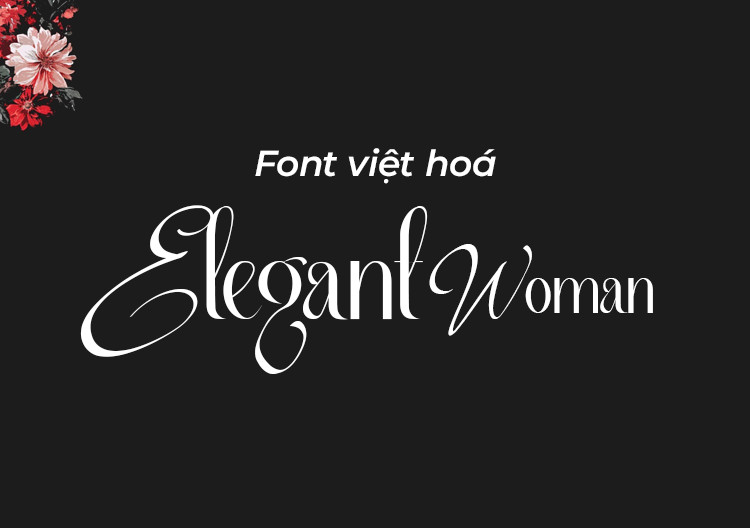
Giới thiệu về Font việt hóa MJ Elegant Woman
Trong thế giới đồ họa hiện đại, việc lựa chọn Font Chữ phù hợp đóng vai trò quyết định đến linh hồn của tác phẩm. Font việt hóa MJ Elegant Woman là một bộ font Serif (có chân) mang phong cách cổ điển, quý phái nhưng không kém phần hiện đại. Được thiết kế với những đường nét mảnh mai, uốn lượn tinh tế, bộ font này mô phỏng vẻ đẹp mềm mại của người phụ nữ, giúp các bản thiết kế trở nên sang trọng và thu hút hơn bao giờ hết.
Đặc điểm nổi bật của bộ font
Bộ font này sở hữu độ tương phản cao giữa các nét thanh và nét đậm, tạo nên nhịp điệu thị giác ấn tượng. Khi sử dụng Font việt hóa MJ Elegant Woman, các nhà thiết kế có thể dễ dàng ứng dụng vào các dự án đòi hỏi tính thẩm mỹ cao như logo thương hiệu thời trang, bìa tạp chí cao cấp, thiệp cưới hoặc các ấn phẩm quảng cáo mỹ phẩm. Đặc biệt, bản việt hóa đã được căn chỉnh kỹ lưỡng về dấu câu, đảm bảo hiển thị hoàn hảo và không lỗi font khi gõ tiếng Việt.
Ứng dụng Font việt hóa MJ Elegant Woman trong học tập và sáng tạo
Gợi ý sử dụng cho học sinh và giáo viên
Không chỉ dành cho chuyên gia, Font việt hóa MJ Elegant Woman còn là công cụ tuyệt vời cho các bạn học sinh khi thiết kế slide thuyết trình hoặc làm báo tường điện tử. Sự rõ ràng và thanh thoát của font giúp nội dung trở nên dễ đọc và chuyên nghiệp. Giáo viên cũng có thể dùng font này để trang trí tiêu đề bài giảng, tạo sự hứng thú và mới mẻ cho học sinh trong mỗi tiết học.